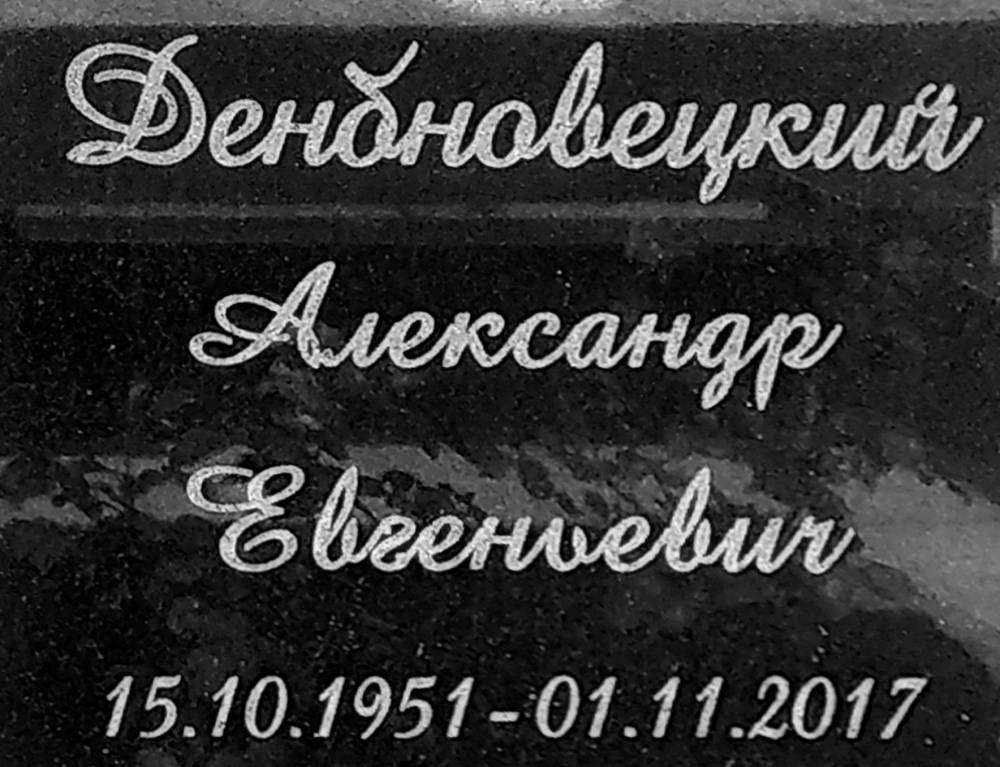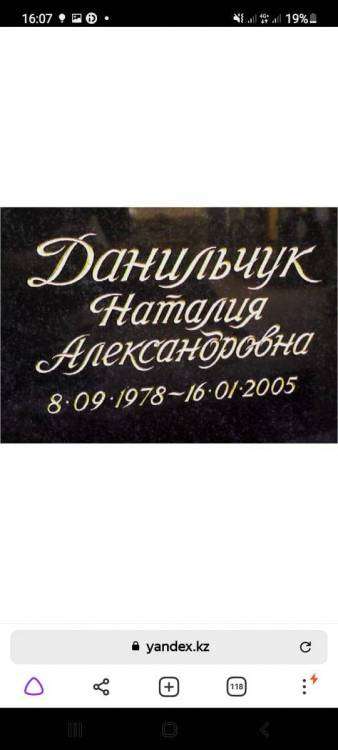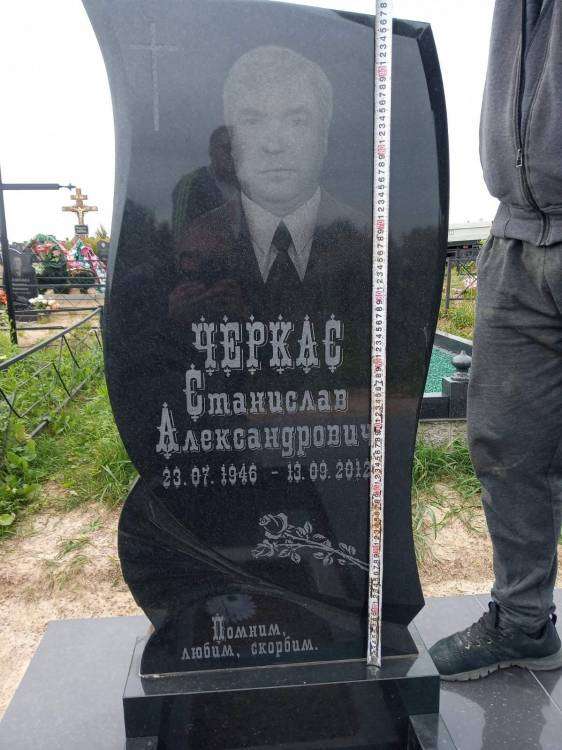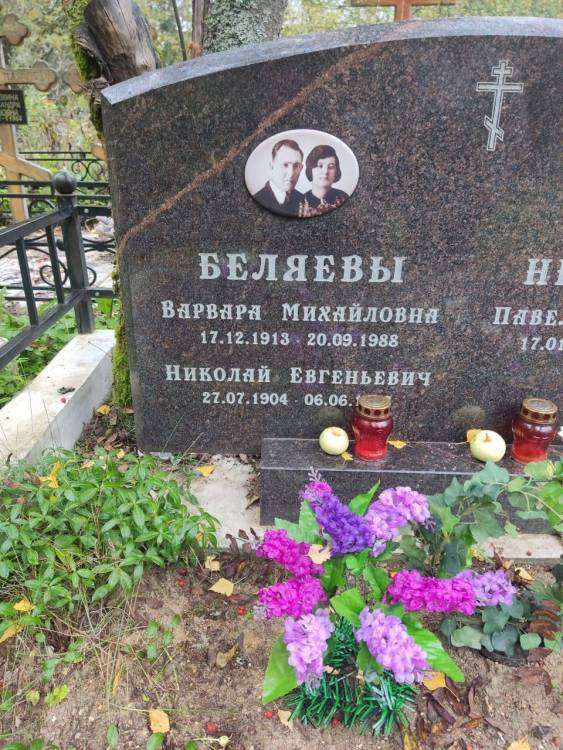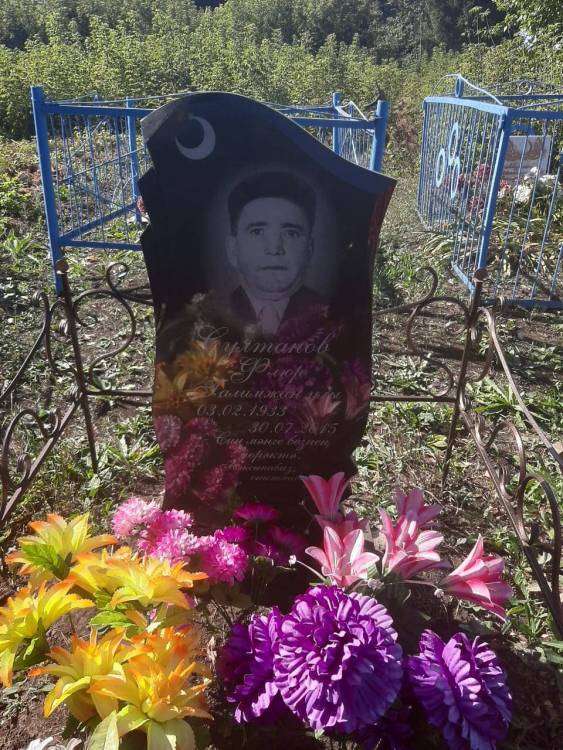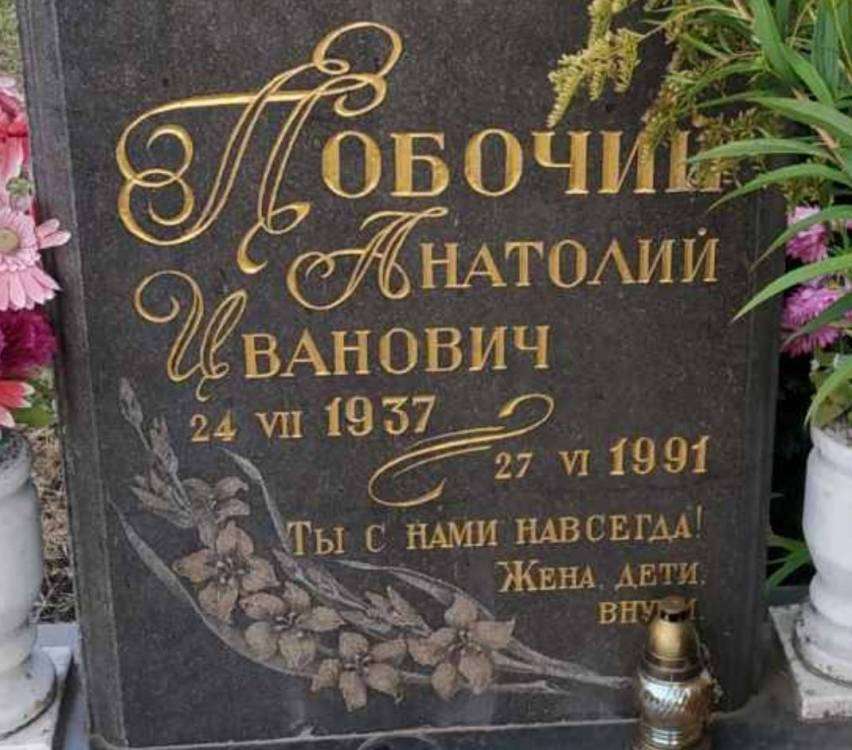
Помогите найти шрифт!
Подскажите шрифт плиззззз
Уже нашёл, всем спасибо)) называется Benguiat
Помогите определить шрифт
такой шрифт
Помогите определить шрифт
такой шрифт не найдёте. это ручник
Помогите найти пожалуйста такой шрифт, с поддержкой татарского языка
@Irina Gaf Cкорее всего вручную придётся двигать и дорисовывать символы..
Можете написать в личку, смогу помочь, если знаете название этого шрифта
помогите , может у кого есть этот шрифт или знает названия , очень нужна копия .  Шрифт типо CyrillicOld, да похожий , но не он :(
Привет всем. Помогите определить название шрифта. Все обыскал - не могу найти. Склоняюсь к частному дизайнеровскому шрифту. Но может кто все же знает.
всем привет. может кто знаком с таким ?))
Помогите найти пожалуйста такой шрифт, с поддержкой татарского языка
Похоже на snell roundhand.
Здравстуйте. Помогите пожалуйста найти шрифт. Я понимаю что скорее всего это ручная гравировка, но возможно кто-то знает хотя бы похожий шрифт. Буду очень благодарный.
Если вы о том, что смотрится объемным,то это не про шрифт.Это настройки стиля слоев в фотошопе. Все эти примочки вы можете применить к любому шрифту.
@Ekaterina941 Ну вот, например, Georgia Bold. На текстовом слое контекстным меню выбираем параметры наложения и применяем "тиснение" Вроде похоже)
Добрый день. Кто знает что за шрифт - помогите. Заранее спасибо. Программа не находит
Это ручной шрифт
Спасибо. Может кто знает приближенный к данному шрифт?